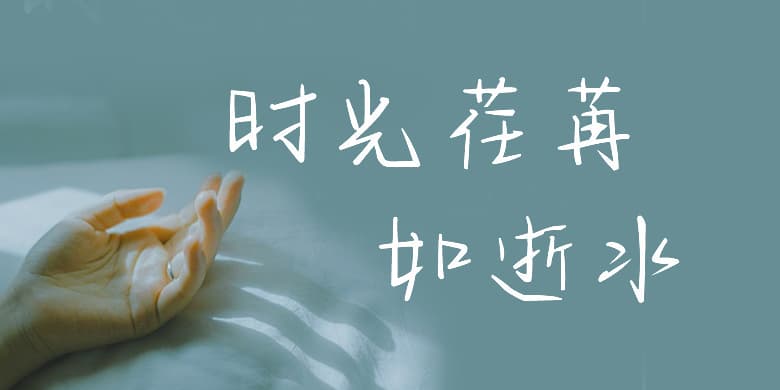
品牌:方正手迹设计师:余丹发行时间:2019字库编码:大陆简体(GB2312-80)分类:常规书写·硬笔字体属性:精品字
如同流水一般的行书笔画,行笔讲究,连笔较多,从容不迫,结构严谨不呆板。粗细变化有致,瘦长中遒劲有力,舒展大方。适用于文艺类的书刊、品牌广告和产品包装设计,以及社交网络的个性化用字。